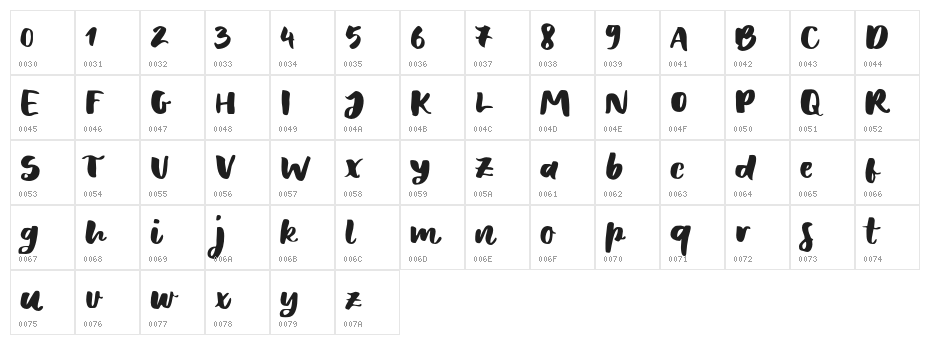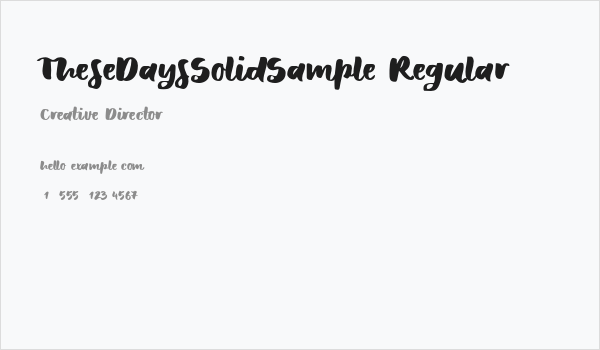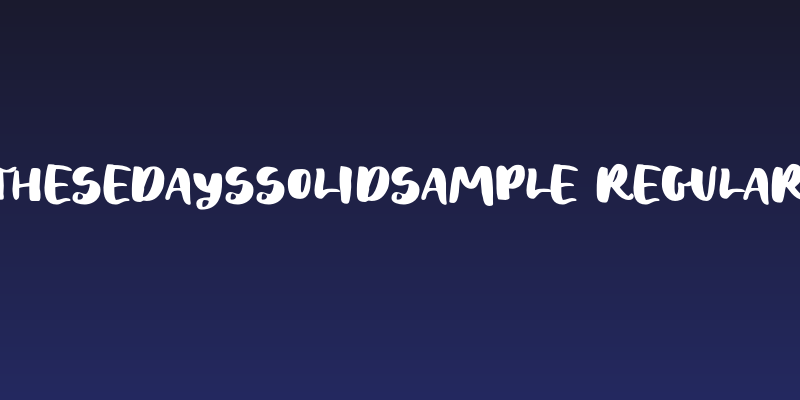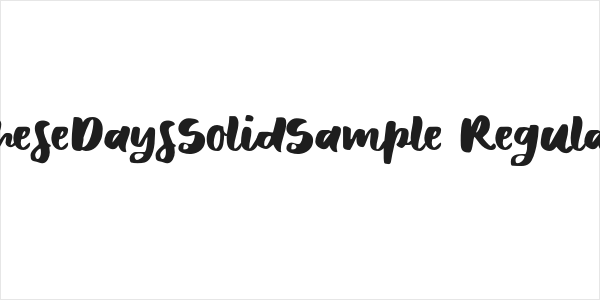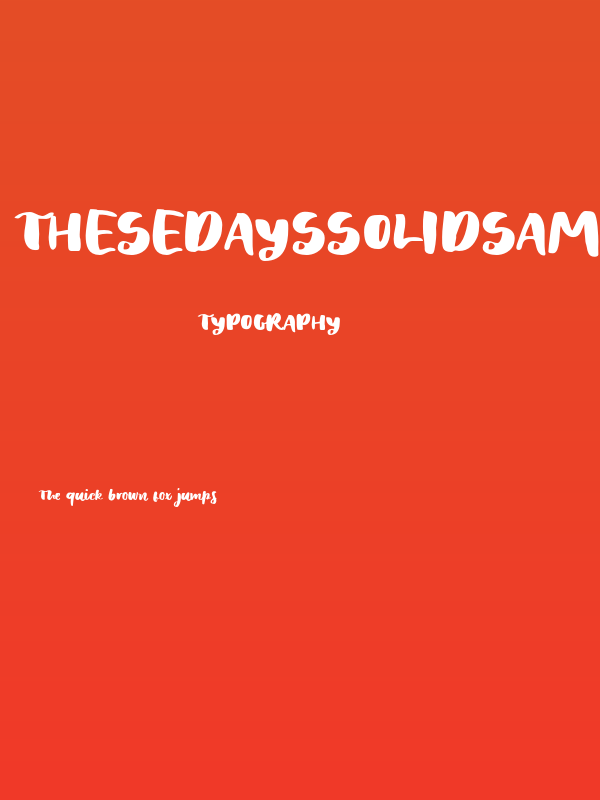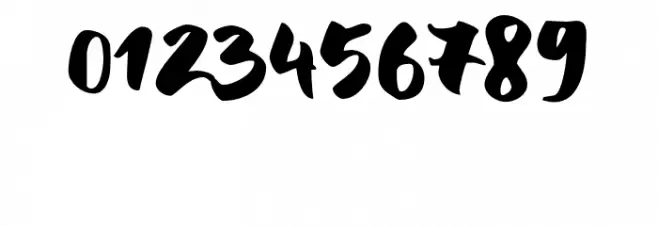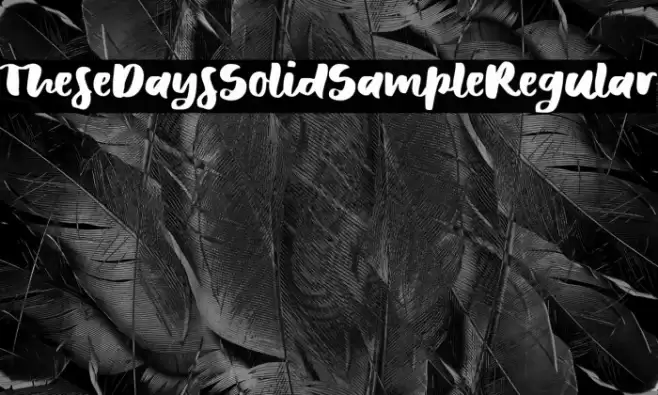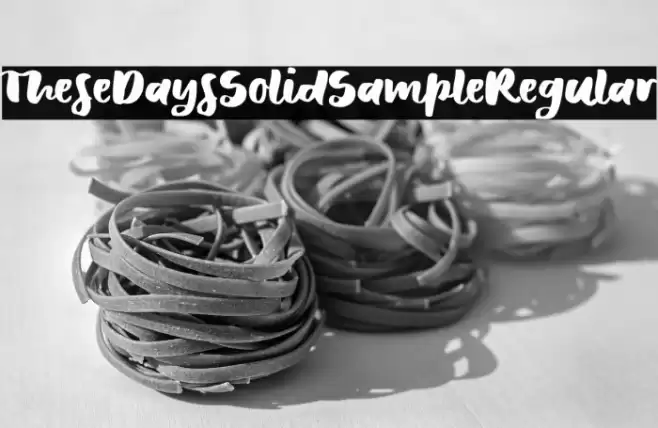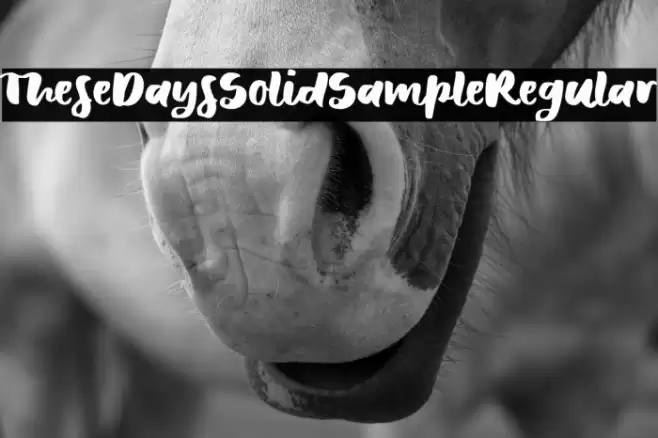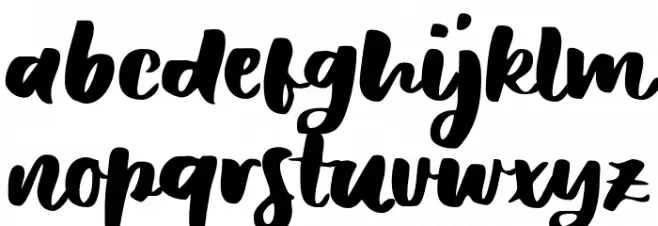
TheseDaysSolidSample-Regular Font
Esta fonte inclui 66 caracteres. Clique em qualquer caractere para ver os detalhes.
| Família da fonte | These Days Solid Sample |
| Projetos propostos | Ideal for branding, posters, social media graphics, and invitations where a personal and modern touch is desired. |